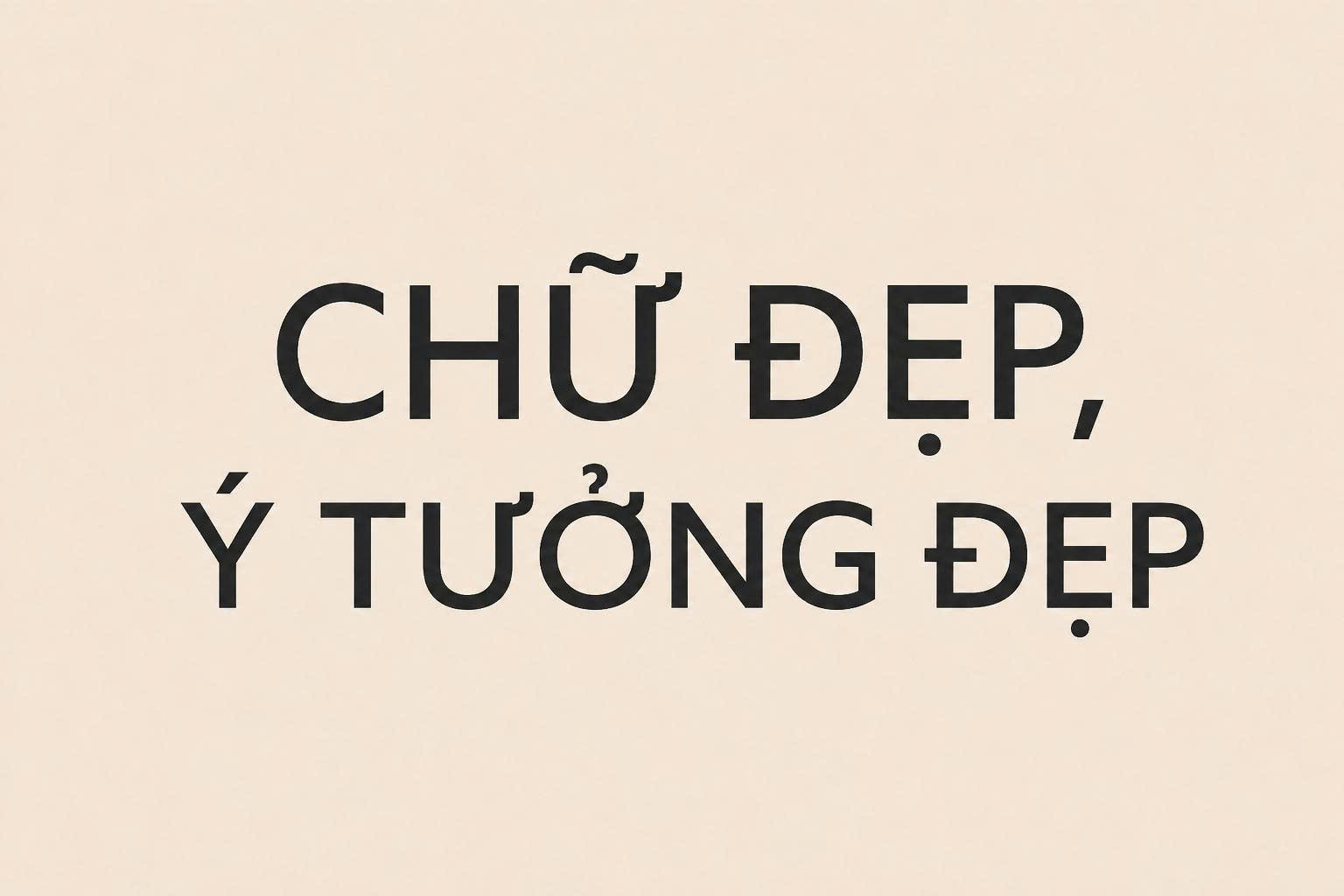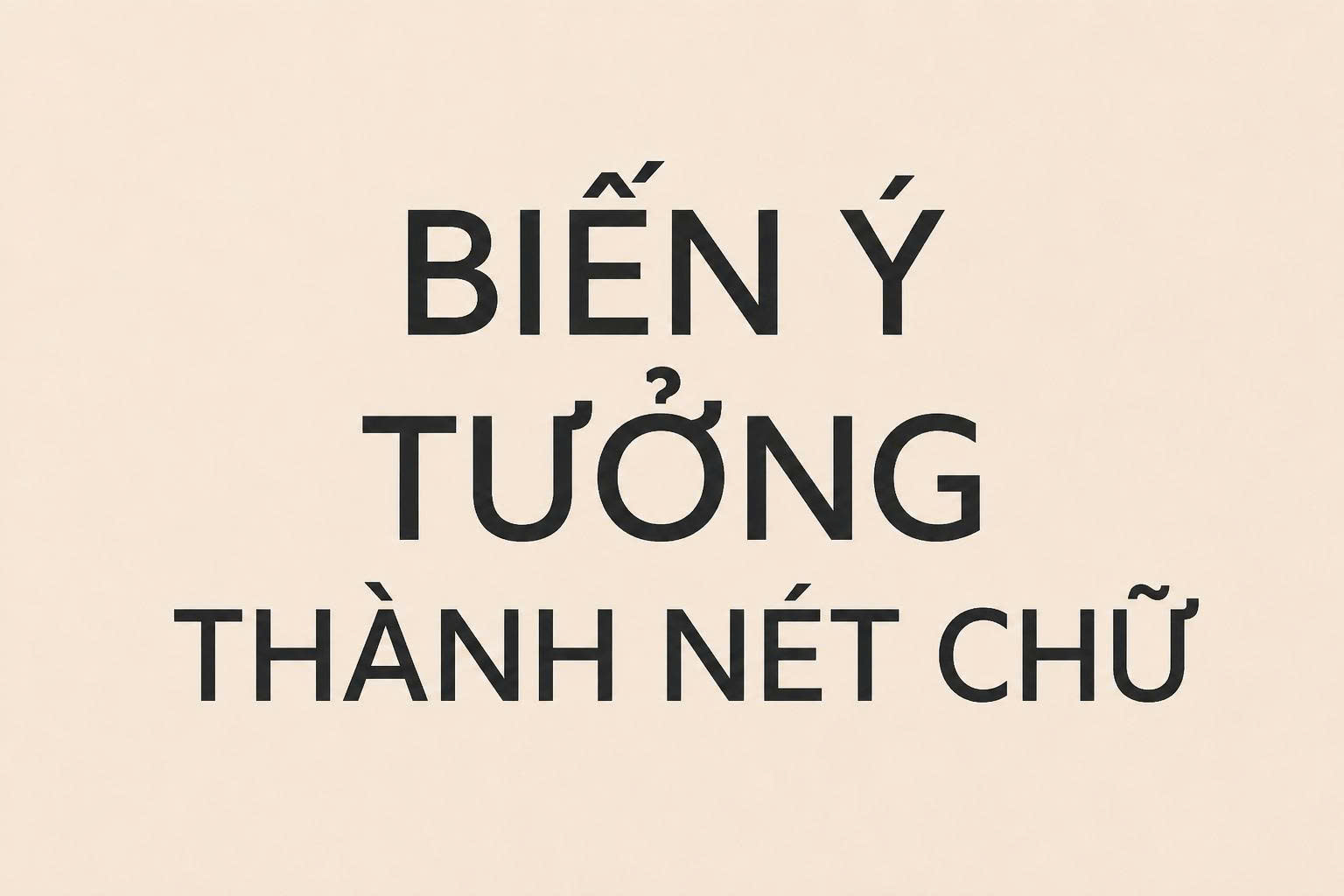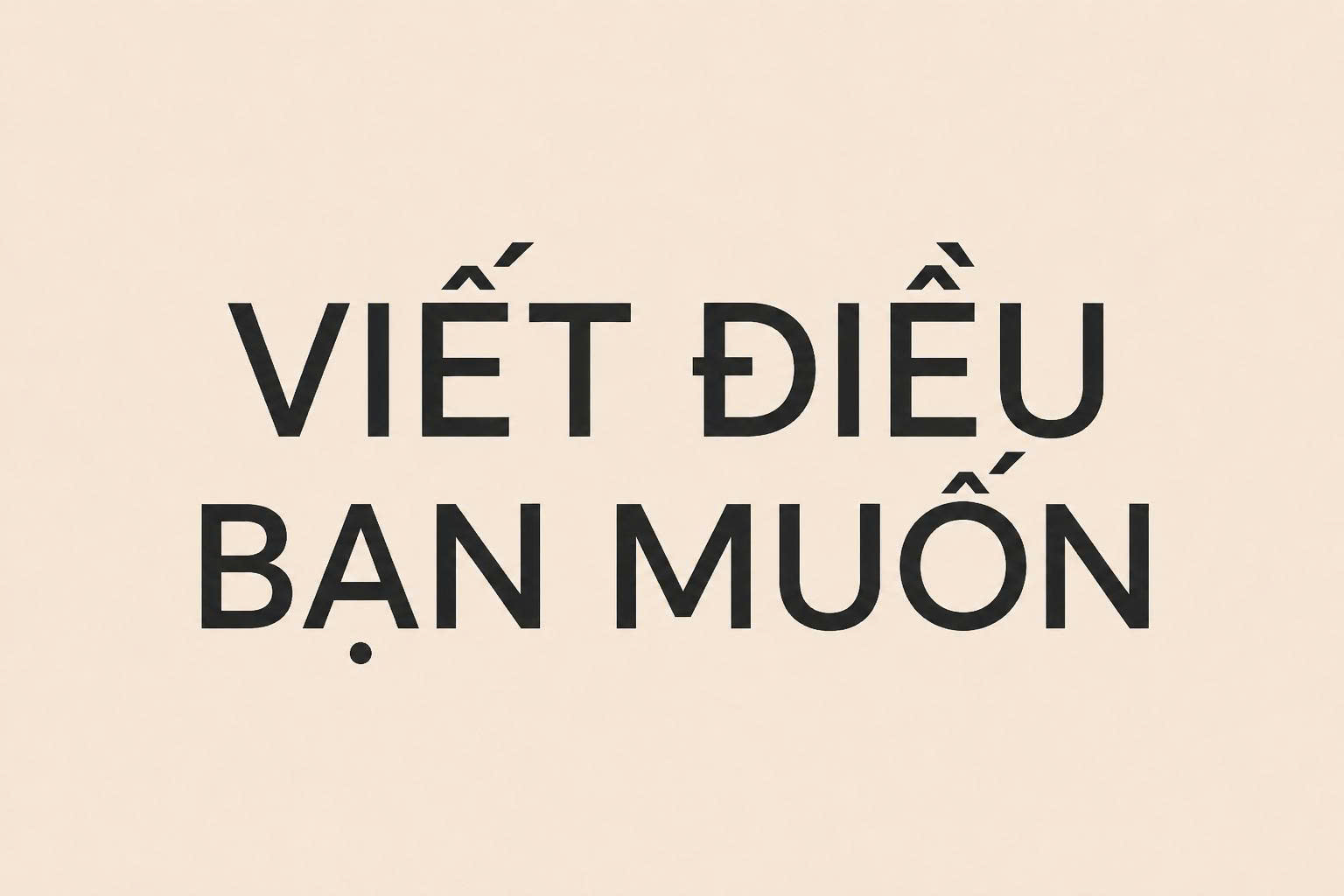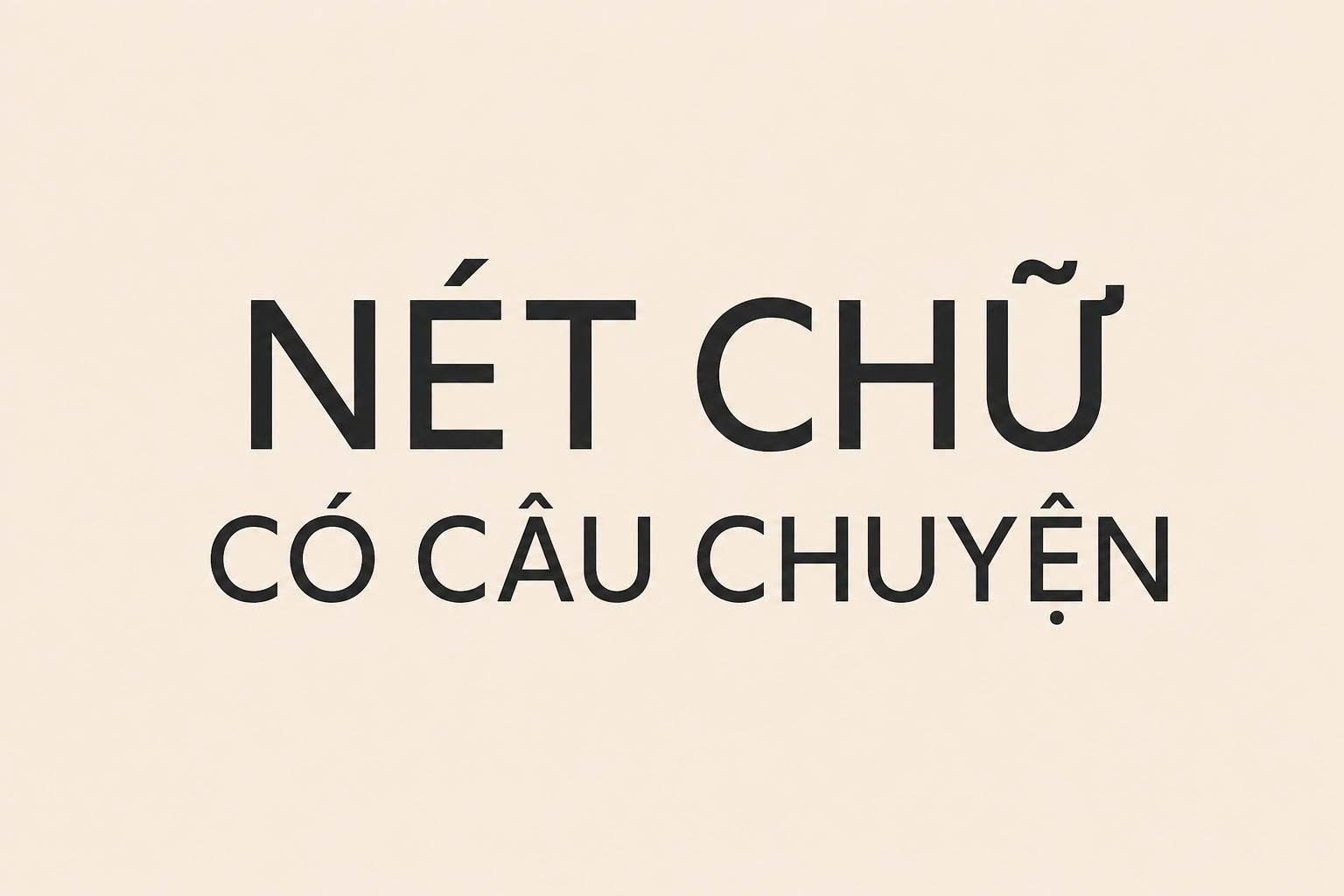
Frutiger font Việt hóa là bộ phông chữ không chân (Sans-serif) nhân văn kinh điển, được thiết kế bởi Adrian Frutiger với mục tiêu tối ưu hóa khả năng đọc hiểu ở mọi khoảng cách và điều kiện ánh sáng. Ban đầu được tạo ra cho hệ thống biển báo tại sân bay Charles de Gaulle, Frutiger đã trở thành biểu tượng của sự minh bạch, uy tín và được ứng dụng rộng rãi trong thiết kế bộ nhận diện thương hiệu toàn cầu. Doozypack.vn chia sẻ link tải font Frutiger Việt hóa chuẩn, giúp bạn sở hữu bộ phông chữ chuyên nghiệp để thiết kế bao bì mà không gặp lỗi dấu tiếng Việt.
Đặc điểm thiết kế vượt trội của bộ font Frutiger Việt hóa
Frutiger không chỉ là một phông chữ hiện đại; nó là kết quả của sự nghiên cứu tâm lý thị giác để mang lại trải nghiệm đọc mượt mà nhất cho người dùng.
Phong cách Humanist Sans-serif dễ đọc tuyệt đối
Đặc trưng lớn nhất của font Frutiger Việt hóa là cấu trúc chữ mở rộng, các nét chữ có độ dày vừa phải và hình khối cân đối. Khác với phông chữ hình học cứng nhắc, Frutiger mang hơi hướng “nhân văn” với các đường cong tự nhiên, giúp mắt người nhận diện ký tự nhanh hơn. Đặc điểm này khiến nó trở thành lựa chọn hàng đầu cho các thiết kế cần truyền tải thông tin quan trọng một cách nhanh chóng và chính xác.
Sự khác biệt rõ rệt giữa các ký tự dễ nhầm lẫn
Trong thiết kế in ấn bao bì dược phẩm hoặc thực phẩm, việc nhầm lẫn giữa chữ “I” (i hoa), “l” (l thường) và số “1” có thể gây ra sai sót thông số kỹ thuật. Frutiger đã giải quyết triệt để vấn đề này bằng cách tạo ra các đặc điểm nhận dạng riêng biệt cho từng ký tự. Khi được Việt hóa tại Doozypack.vn, hệ thống dấu thanh được tinh chỉnh để không làm che khuất các khe hở trong chữ, đảm bảo văn bản luôn thông thoáng.
Tại sao designer nên chọn font Frutiger tiếng Việt cho bao bì?
Trong ngành sản xuất bao bì giấy tại Doozypack.vn, Frutiger luôn nằm trong danh mục “font chữ an toàn” cho các dự án chuyên nghiệp:
- Giải quyết lỗi hiển thị tiếng Việt: Việc sử dụng bản font Frutiger tiếng Việt chuẩn giúp bạn gõ các từ khóa kỹ thuật như “Thành phần”, “Hướng dẫn bảo quản” một cách trọn vẹn, không bị lỗi nhảy font ở các ký tự có dấu.
- Tính ứng dụng đa năng: Bạn có thể dùng Frutiger cho cả tên thương hiệu chính lẫn các khối văn bản nhỏ ở mặt sau hộp giấy mà vẫn đảm bảo tính thẩm mỹ đồng bộ.
- Khẳng định uy tín thương hiệu: Vẻ ngoài hiện đại và trung tính của Frutiger mang lại cảm giác tin cậy, bền vững cho doanh nghiệp.
| Biến thể Font | Đặc điểm thị giác | Ứng dụng đề xuất tại Doozypack.vn |
| Frutiger Light/Roman | Thanh mảnh, thanh lịch | Dùng cho nội dung hướng dẫn sử dụng, địa chỉ sản xuất. |
| Frutiger Medium/Bold | Vững chãi, rõ nét | Dùng cho tiêu đề phụ, các lưu ý quan trọng trên bao bì. |
| Frutiger Black | Rất đậm, nổi bật | Dùng làm Logo hoặc tên sản phẩm chính trên mặt trước vỏ hộp. |
Gợi ý lựa chọn: Đối với các bản in trên túi giấy Kraft có bề mặt thô nhám, Doozypack.vn khuyên bạn nên sử dụng biến thể Frutiger Medium thay vì Roman để đảm bảo nét chữ không bị “nuốt” mực, giúp thông tin hiển thị sắc nét hơn.
03 Ứng dụng của font Frutiger trong sản xuất bao bì tại Doozypack.vn
Sự minh bạch và hiện đại của Frutiger mang lại hiệu quả thị giác đặc biệt trên các ấn phẩm thực tế:
- Bao bì Dược phẩm & Thiết bị y tế: Độ dễ đọc cực cao của Frutiger giúp người dùng dễ dàng tra cứu liều lượng và cách dùng trên những hộp thuốc kích thước nhỏ.
- Hộp sản phẩm Công nghệ: Nét chữ sạch sẽ của Frutiger rất phù hợp với phong cách tối giản của các linh kiện điện tử cao cấp.
- Túi giấy Doanh nghiệp: Tên công ty in bằng font Frutiger trên túi giấy Ivory cán màng mờ mang lại diện mạo vô cùng chuyên nghiệp và chỉn chu.
03 Lưu ý kỹ thuật khi in ấn với phông chữ Sans-serif như Frutiger
Sản xuất bao bì sử dụng phông chữ như Frutiger đòi hỏi designer cần lưu ý một số vấn đề kỹ thuật tại xưởng in chuyên nghiệp:
- Kiểm soát kích thước chữ tối thiểu: Trên chất liệu giấy Ivory phẳng mịn, Frutiger vẫn rõ nét ở 5.5pt. Tuy nhiên, trên giấy có gân hoặc giấy thô, hãy để tối thiểu là 7pt để các dấu tiếng Việt không bị nhòe màu.